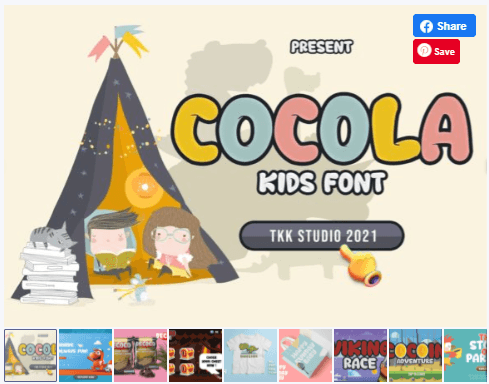
COCOLA - kids font
Cocola - это крутой и яркий дисплейный шрифт. Он олицетворяет игривость и аутентичность и является идеальным выбором для любого детского мероприятия или школьного проекта.